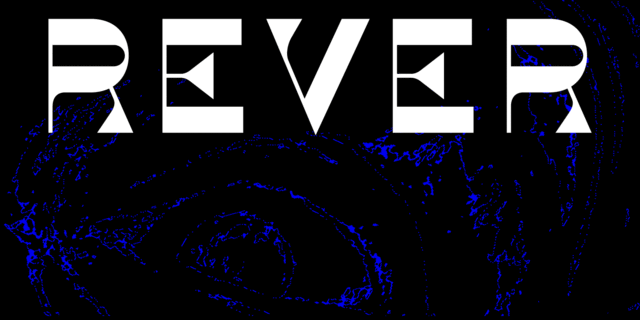
Rever — экспериментальный шрифт молодого дизайнера Саши Смирнова. Он, с одной стороны, недвусмысленно намекает на шрифты XIX века с обратным контрастом, но с другой — форма знаков сделана максимально простой и геометричной. Это один из ответов на вопрос «Каким сегодня может быть шрифт с обратным контрастом?» В Rever нестандартный набор начертаний: кроме прямого, есть ещё наклонное (влево, а не вправо!) и трафаретное. Шрифт подойдёт для типографических экспериментов в любой среде — вебе, печати или моушен дизайне. Шрифт выпущен компанией Паратайп в 2019 году.